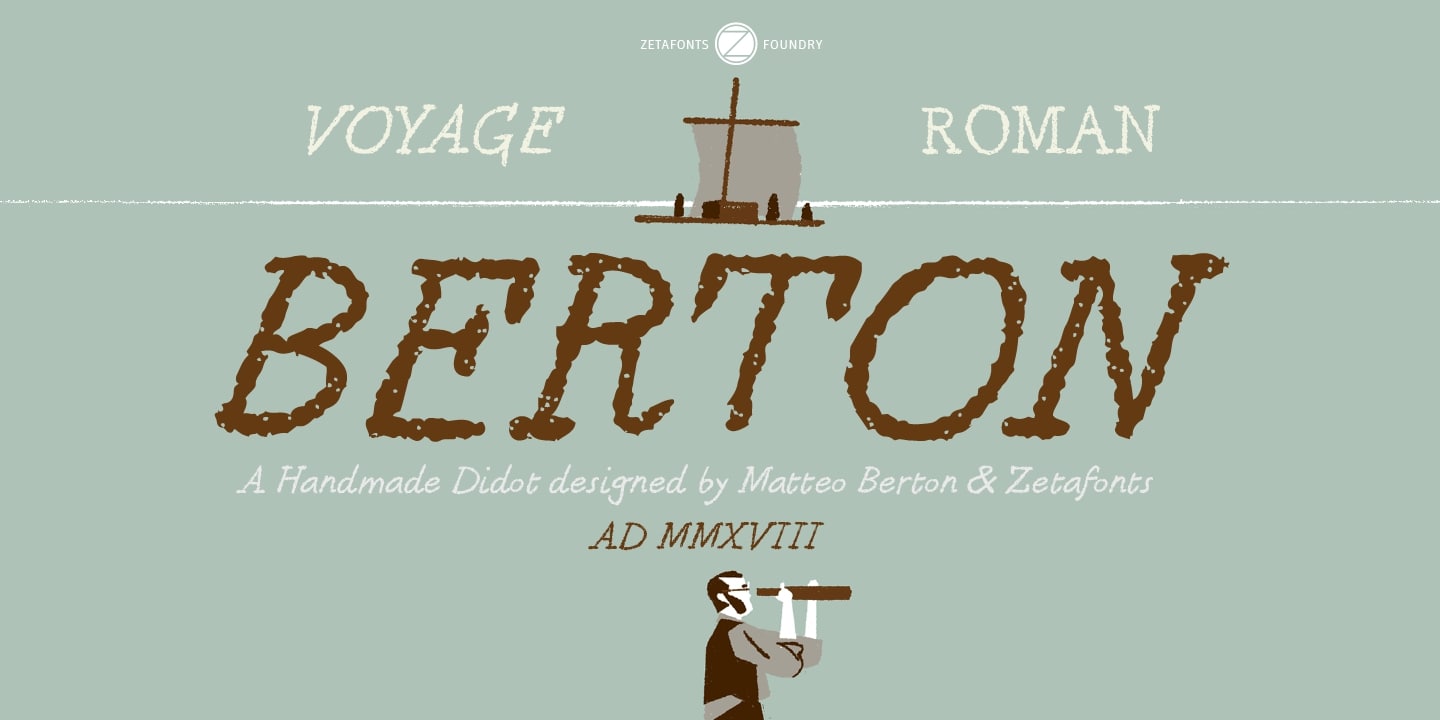
Шрифт Berton
Это выразительный каллиграфический шрифт с эффектом маркера, разработанный итальянским иллюстратором Маттео Бертон (Matteo Berton) и оцифрованный студией Zetafonts. Изначально созданный как основной для графического романа «Путешествие в центр Земли», он обладает динамичным характером, неровными краями и имитирует ручной рисунок. Шрифт поддерживает кириллицу, сохраняя естественность начертания букв даже в сложных сочетаниях. Отлично подходит для заголовков, постеров и акцидентной печати. Скачать бесплатно можно по ссылке ниже